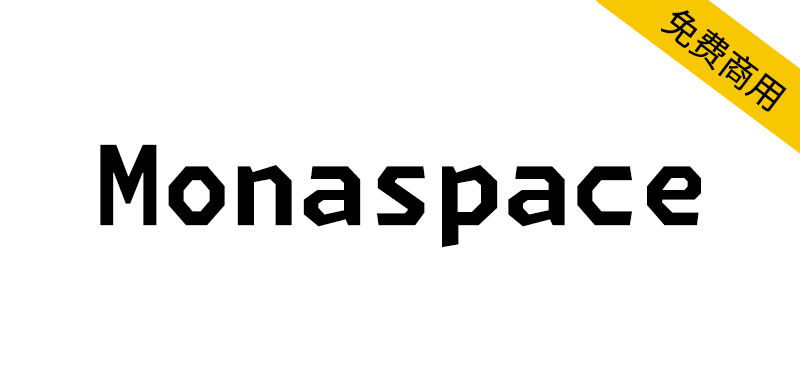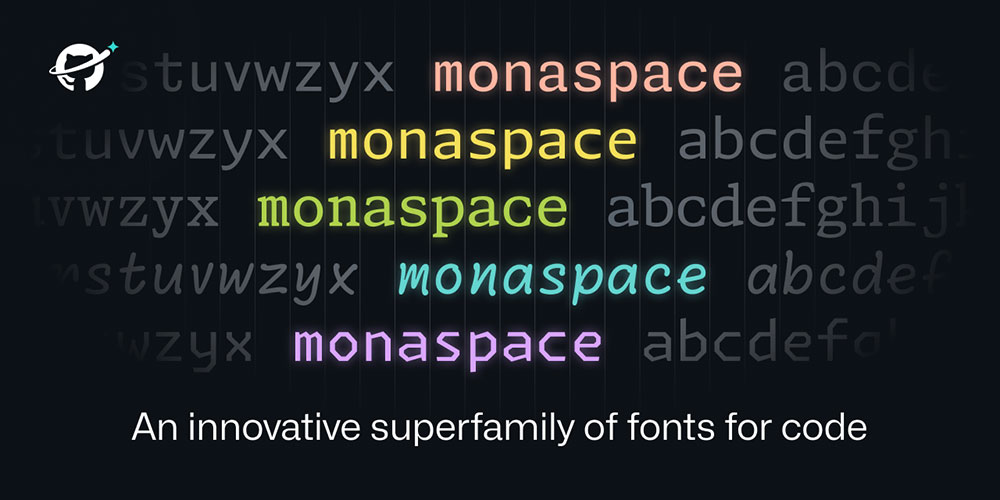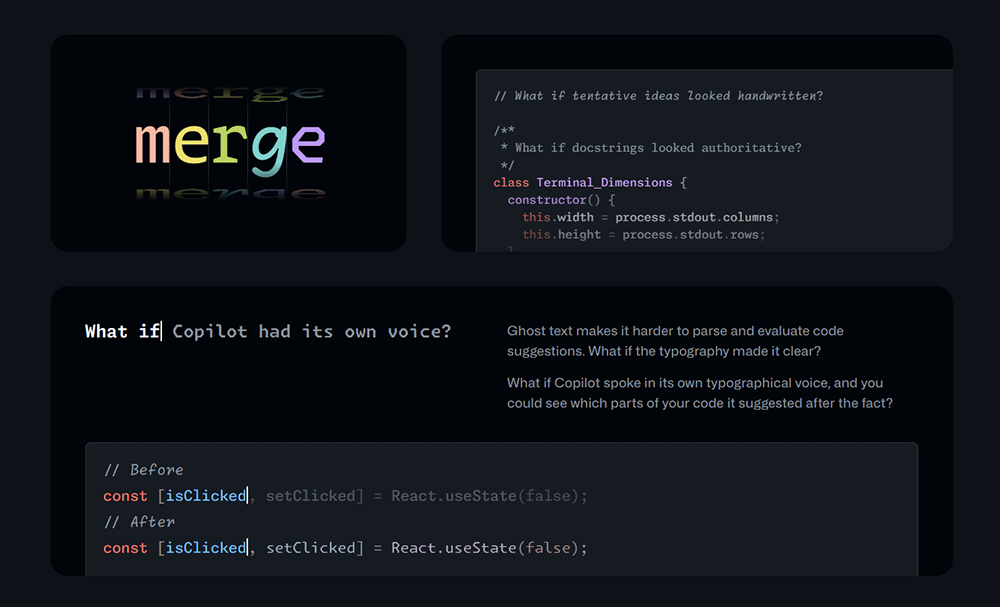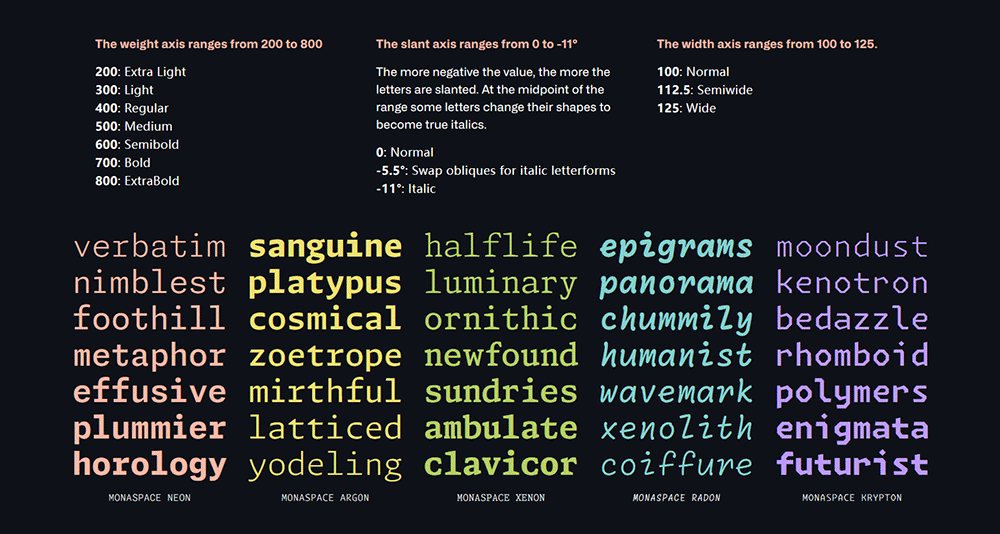
Monaspace字体是一套暗藏现代玄机的等宽字体超级家族,Monaspace字体家族拥有五款不同风格的字体和3个可变轴,这五款字体分别为Monaspace Neon(现代风格字体)、MonaspaceArgon(人文风格字体)、Monaspace Xenon(衬线风格字体)、Monaspace Radon(手写风格字体)、Monaspace Krypton(机械风格字体),每款字体都拥有独特个性,但彼此间完全保持互相兼容,让你能自由混搭组合,打造更具表现力的排版效果。这五款字体均支持调节字重,特别适合 IDE(集成开发环境) 使用,可以让 IDE 附有表现力,也可以作为系统字体日常使用,或是应用到科技风设计当中。
自电传打字机时代起,代码便以等宽字体呈现——网格之上,字字对齐。Monaspace这一新型字体系统,将代码屏幕显示的工艺水准推向全新高度。
计算技术的每次飞跃,都伴随着代码显示与编辑方式的革新。阴极射线管催生了屏幕编辑器,图形用户界面的出现孕育了集成开发环境。
即便在今天,当我们试图为代码赋予额外语义时,选择依然有限。语法高亮技术诞生于1982年,最初只为帮助儿童学习BASIC语言。但除了色彩变化,大多数编辑器仍只能通过悬停提示、下划线等界面元素与开发者沟通。Monaspace为代码及开发工具提供了更富表现力的视觉语言体系。
等宽字体:等宽字体通常彼此互不兼容。每种字体采用不同的度量标准,导致无法混合使用不同字体。而Monaspace系列的每款字体都经过精心设计,可实现无缝混排搭配。通过超越常规色彩与加粗字重的多样化组合,为代码赋予更丰富的语义层次。构建需要更强结构性与层级感的代码界面。
纹理修复:等宽字体存在一个固有缺陷——文本纹理不均匀,某些区域显得过于密集,而另一些区域则留白过多。这是将所有字母强行塞进统一宽度的方框时不可避免的结果,毕竟不同字母对空间的需求本就不同。
自20世纪60年代电传打字机的鼎盛时期以来,这些缺陷始终未变。而Monaspace字体的纹理修复特性(Texture Healing)是一项创新技术,它能平衡等宽字体的视觉密度,使其更接近比例字体沿用数百年的优雅形态。 纹理修复技术严格保留等宽网格特性,无需新软件或编辑器插件即可在多数编程环境中生效。
编程连字:Monaspace 字体为多种编程语言提供了代码连字功能,这些连字按风格集(stylistic sets)分类,您可根据个人偏好自由启用或禁用。
每个风格集大致围绕特定语言的需求设计。例如,ss01 包含 JavaScript 中常见的字符序列连字,而 ss05 则提供 F# 运算符的连字组合,您可以按需启用任意数量的风格集,除八组风格集外,还有两项额外的 OpenType 功能可供开启:
calt(上下文替代):激活纹理修复(Texture Healing)技术
liga(标准连字):优化重复字符(如///或||)的间距,并设计为在较长序列(如////)中自动禁用